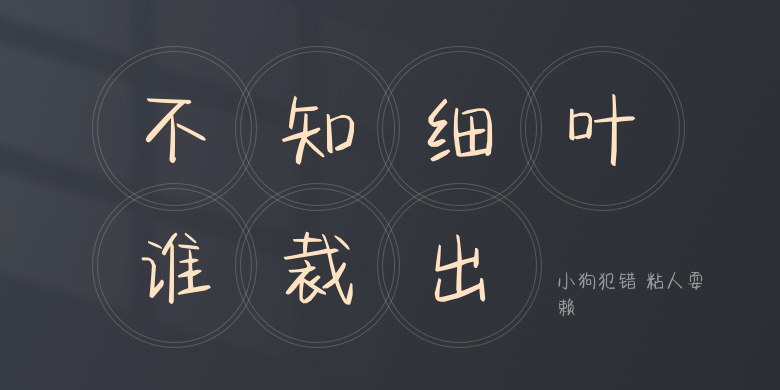
小狗犯错 粘人耍赖
小狗犯错 粘人耍赖,这款字体结构工整、笔画清晰,兼顾美观与易读性,适用于标题、正文、海报、包装、LOGO 等多种场景。字形优雅稳定,风格百搭耐看,适配日常排版与创意设计,让文字呈现更舒适、更具质感。小狗犯错 粘人耍赖一笔一画,皆是细节,以均衡的比例、流畅的线条打造舒适视觉体验,字形端正大气,风格简约现代。无论是商业设计、品牌宣传还是日常排版,都能轻松驾驭,让文字更有格调与力量。小狗犯错 粘人耍赖字体下载。